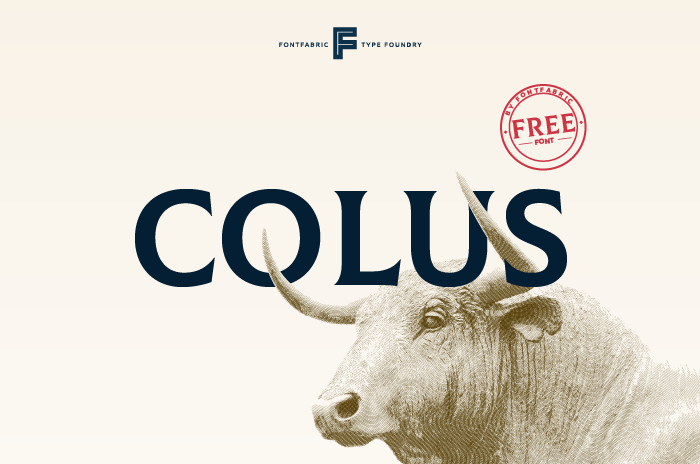
Colus Typeface – Fonte Grátis
Colus Typeface
A Colus Typeface é uma fonte serifa introduzida por Stan Partalev inspirada nas inscrições carregadas de letras encontradas nos monumentos de pedra e madeira. Com uma aparência clássica e características maduras, essa família de fontes é perfeita para headlines impactantes, logotipos memoráveis e sinalização atraente. Assegurando-se da ampla suporte linguístico latino-círtico, localizações adequadas e linhas numéricas com o estilo antigo nas linhas do texto, Colus é uma inovação na categoria de fontes profissionais por Stan. Sua introdução como a primeira fonte profesionalmente desenvolvida pelo autor coloca Colus no topo da gama. A presença em múltiplos idiomas e seus recursos práticos tornam-se um verdadeiro ativo para qualquer designer ou projetista gráfico, dando-lhe a liberdade de escolher entre uma ampla variedade de opções visuais que vão desde as inscrições em monumentos até design editorial sofisticado. Engenhosamente planejada e cuidadosamente criada, Colus é uma excelente adição ao seu arsenal de ferramentas digitais para criar projetos de design memoráveis.